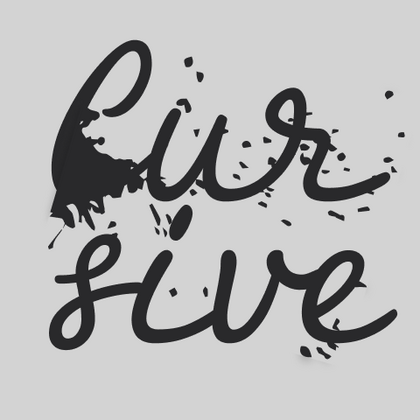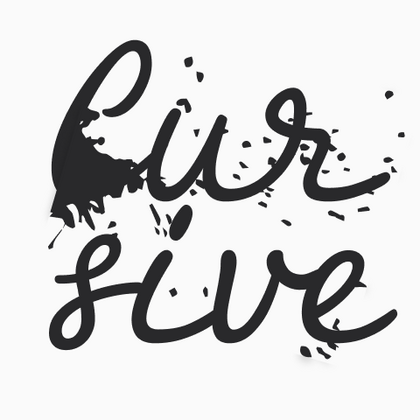
Рукописные шрифты
Эти шрифты также называют script fonts. Их рисунок имитирует человеческий почерк — буквы выглядят так, будто написаны от руки. При этом рукописные шрифты могут быть совершенно разными по характеру: элегантными или дерзкими, строгими или весёлыми, создавать лёгкое, игривое настроение или ощущение историчности и принадлежности к прошлому. Ниже представлены рукописные шрифты из коллекции TypeType.
TT Disruptors — дуктальный рукописный шрифт, созданный с помощью маркера. Его рисунок уникален: потёртости, неравномерная толщина штрихов и удлинённые выносные элементы придают ему живую, динамичную текстуру и ощущение рукотворности. Характер этого шрифта своенравный и эмоциональный, но при этом тёплый и душевный.